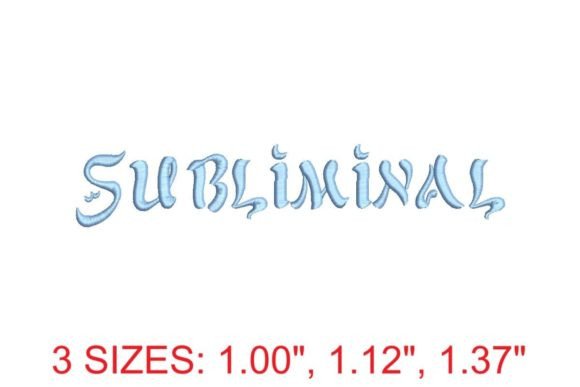
Subliminal Medium Embroidery Font
Mencari elemen reka bentuk yang sesuai boleh menjadi mencabar, tetapi Subliminal Medium Embroidery Font menawarkan koleksi luar biasa yang menaik taraf karya anda serta-merta.
Dicipta dengan ketepatan, Subliminal Medium Embroidery Font menyediakan vektor yang bersih, tipografi yang licin dan lesen komersial untuk ketenangan fikiran.
Sama ada anda mencipta produk POD (Print on Demand), jemputan perkahwinan atau grafik media sosial, Subliminal Medium Embroidery Font amat bersesuaian.